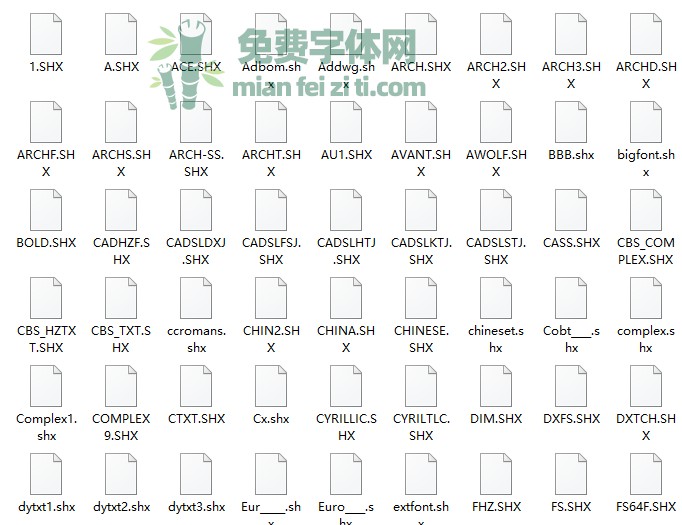
cad字体打包 共275个SHX格式字体
cad字体打包里一共包含了275个常用cad字体文件。均为shx格式,这些字体主要作用就是方便建筑工程人员查看图纸。如果系统中缺少了某个cad字体的话将导致图纸无法正常打开查阅,如出现乱码等现象。因此安装完整的cad字体是有必要的!
AutoCAD字体使用技巧:
首先,同样是在够用情况下,越少越好的原则。这一点,应该适用于CAD中所有的设置。不管什么类型的设置,都是越多就会造成 CAD文件越大,在运行软件时,也可能会给运算速度带来影响。更为关键的是,设置越多,越容易在图元的归类上发生错误。另外,在使用CAD时,除了默认的 Standard 字体外,一般只有两种字体定义。一种是常规定义,字体宽度为 0.75。一般所有的汉字、英文字都采用这种字体。第二种字体定义采用与第一种同样的字库,但是字体宽度为 0.5。这一种字体,是我在尺寸标注时所采用的专用字体。因为,在大多数施工图中,有很多细小的尺寸挤在一起。这时候,采用较窄的字体,标注就会减少很多相互重叠的情况发生。不要选择前面带“@”的字体,因为带“@”的字体本来就是侧倒的。可以直接使用 Windows 的 TTF 中文字体,但是 TTF 字体影响图形的显示速度,还是尽是避免使用它们。